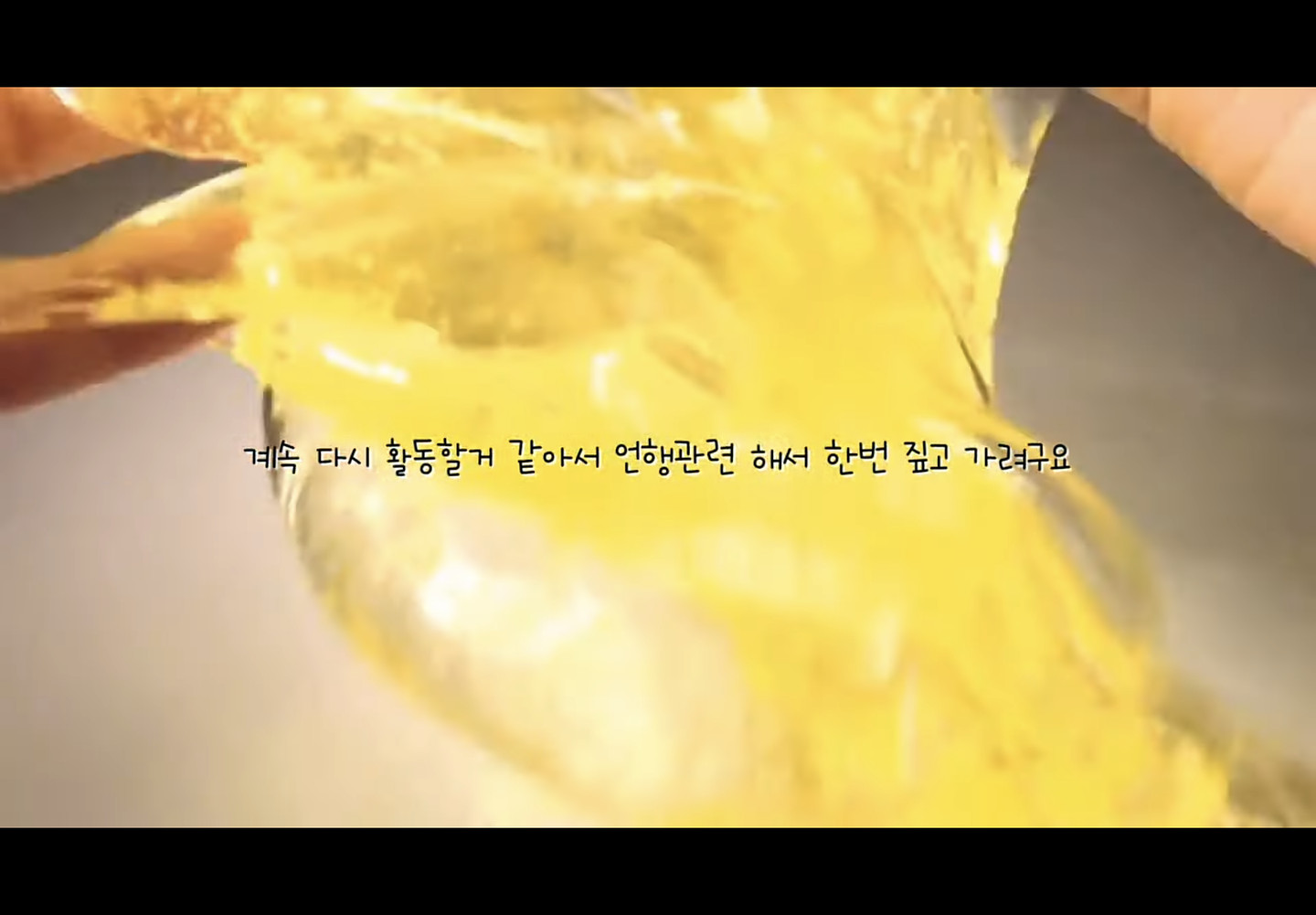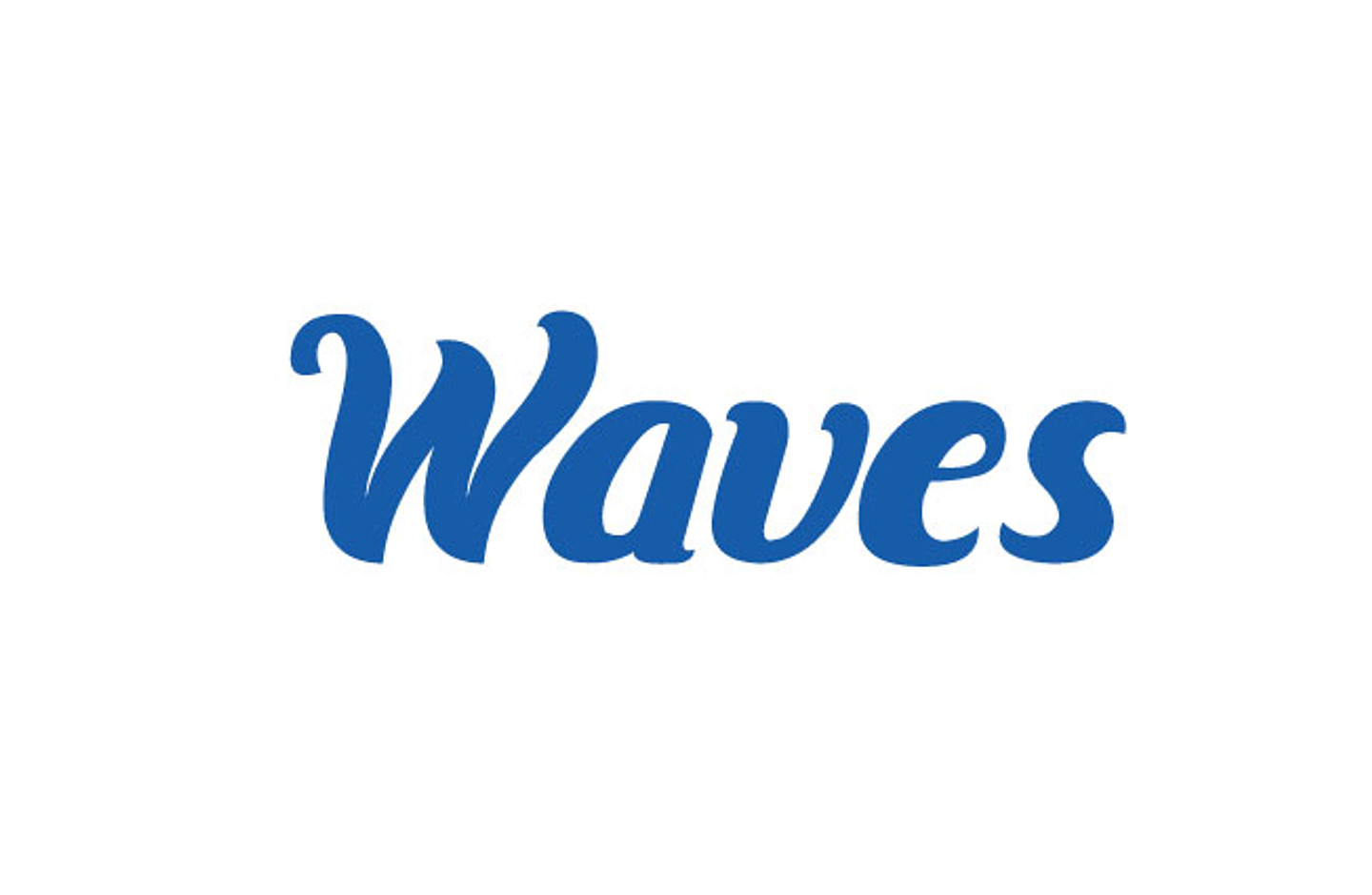
요기 폰트 이름이 뭔가요! 최대한 빨리 답변 부탁드리구 파연카로 알고 잇ㅇ어요!
이 고딕 폰트 정보 알고 싶어요
화질이 깨지긴 하지만 어떤 폰트 인가요?ㅜㅠㅠ급합니다
폰트 넘 궁금해요!!
이거 무슨 폰트일까요 요즘 자주 보이던데
이거 무슨 폰트인지 알 수 있을까용
폰트 문의합니다.
서체 이름을 알려주세요
요정재형 유튜브 폰트 아시는분~ㅜㅜ 프리텐다드랑 비슷한데 얄쌍하거든요. 진짜 다뒤져도 못찾았어요... 그나마 최대한 비슷하게라도 제가찾은 방법은 프리텐다드 폰트에서 X축 크기를 90%로 줄이는 것 뿐인데.. 그건 아닌거 같아요.. 아시는분 ㅠㅠㅠㅠㅠㅠㅠㅠㅠㅠ꼭좀 답변 남겨주시면 감사드리겠습니다ㅠㅠㅠ플리즈ㅠㅠ
동글동글한 손글씨 느낌
이 폰트 아시는 분 계신가요??
무슨 폰트인지 알려주시면 감사드릴게요
글씨체 궁금해요 ㅎㅎ (출처: 포테이토 터틀 유튜브)
글씨체 궁금해요~! (출처: 포테이토 터틀 유튜브)
무슨 폰트일까요???
이거 호깃 무슨 폰트 인가요?